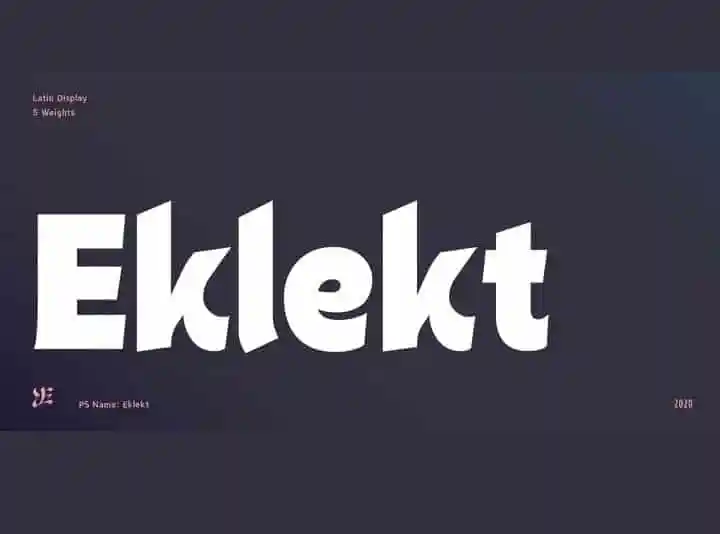
A Eklekt Sans Serif Font é uma moderna releitura dos estilos de fontes retro. Desenhada e compartilhada pelo Yinon Ezra, ela traz a Magia do Eklekt através da combinação perfeita de formas gráficas aguçadas e curvas fluídas que parecem ter sido escritas à mão. É uma escolha versátil para logotipos, headlines e texto curto. Seu design simples, porém poderoso, encaixa-se em qualquer projeto onde um estilo limpo e moderno é desejado. Esta fonte de serif sem serif oferece tanto o visual tradicional quanto a modernidade que tanto as organizações buscam atualmente. Experimente Eklekt para adicioná-lo ao seu design gráfico e dar uma nova cara aos projetos.